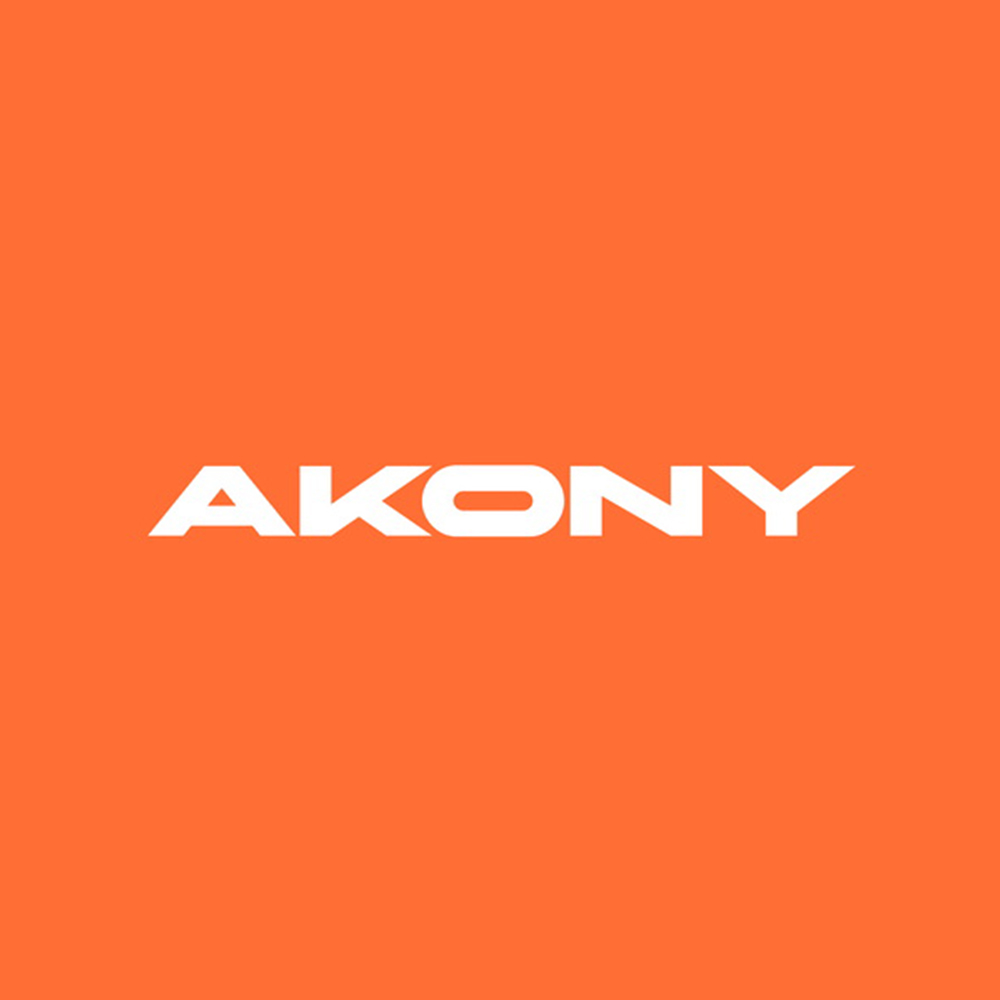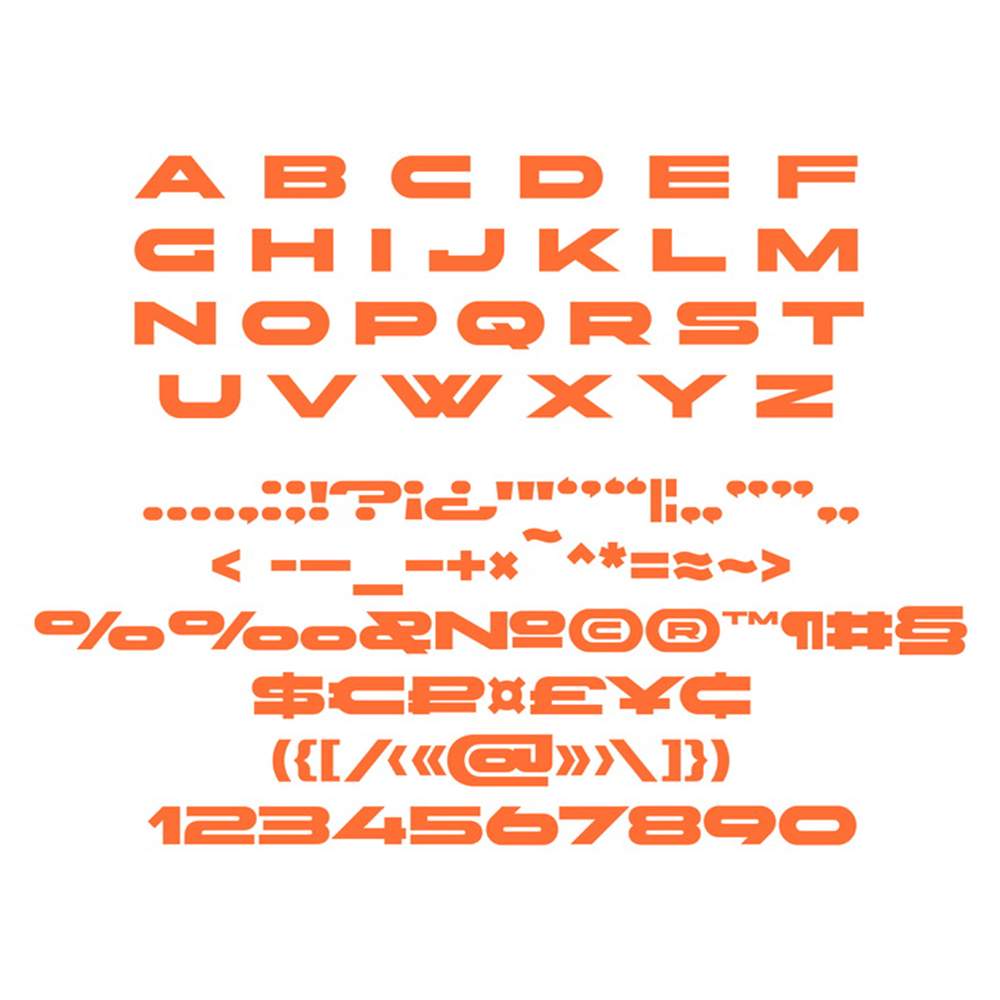
فونت پرمیوم و انگلیسی Akony Font یک فونت تماماً بزرگ از ولادیمیر کلنوف (Vladimir Klenov) است که بدنهی بسیار برجستهای دارد، اما همچنان کنتراست بالایی دارد. این فونت با الهام از سبک طراحی محبوب امروزی، پاسخی به تمام نیازهای هر ایدهای است که در این دوران مدرن خواهید داشت، با سبکی ضخیم و محکم در هر حرف، گویی این فونت روح دارد.
مزایای استفاده از فونت لاتین Akony چیست؟